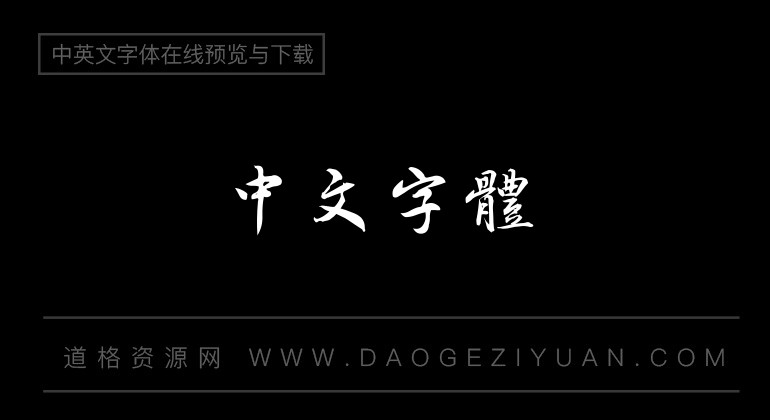
方正字迹-吕建德行楷繁体
方正字迹-吕建德行楷繁体字体是一款由方正字迹设计的繁体楷体字体,由重要的繁体楷体大师吕建德先生设计而成。字体采用繁体书法的精细绘制,让字体更加精致大气,更具有书法艺术感。字体结构紧凑,笔画流畅,更具有视觉冲击力,同时也保留了中国传统文化的色彩,更加贴近中国传统文化的美感。
方正字迹-吕建德行楷繁体是一款非常不错的手写艺术字体,具有很好的视觉感,适合于文化类的宣传设计、商业类品牌的广告和产品包装设计以及个性化文字排版等较多场景。